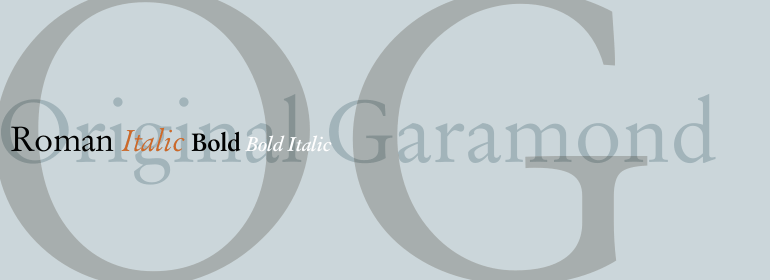
Original Garamond
Original Garamond,这款字体结构工整、笔画清晰,兼顾美观与易读性,适用于标题、正文、海报、包装、LOGO 等多种场景。字形优雅稳定,风格百搭耐看,适配日常排版与创意设计,让文字呈现更舒适、更具质感。Original Garamond一笔一画,皆是细节,以均衡的比例、流畅的线条打造舒适视觉体验,字形端正大气,风格简约现代。无论是商业设计、品牌宣传还是日常排版,都能轻松驾驭,让文字更有格调与力量。Original Garamond字体下载。